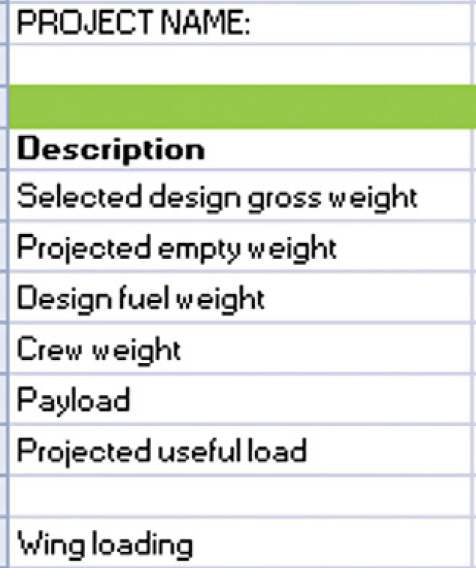
Das ist kein Truetype, OpenType oder Typ1-Font, sondern eine Pixelschrift.
Das bedeutet, das nicht die Außenkonturen der Buchstaben, sondern die einzelnen schwarzen Pixel als Bits in der Schrift gespeichert sind.
Vor Einführung der Truetype-Schriften waren diese auch auf dem PC die gängige Schrifart, und wurden auch von allen Anwendungen unterstützt. Heute noch ist mit dem Betriebssystem eine ganze Reihe dieser Pixelschriften installiert, um so auch alte Software zu unterstützen. Von Grafik, DTP  und Textverarbeitungprogrammen können diese jedoch heute nicht mehr genutzt werden. Bondrucker jedoch verwenden diese wegen der einfachen Umsetzung zum Druck noch immer.
Es gibt zwar einige Trutype-Schriften, die das Erscheinungsbild von Pixelschriften nachzuahmen versuchen, da dann aber die Konturen dieser Rechtecke fast nie mit dem Ausgabe-Raster übereinstimmz, ist deren Bild, gerade auf Bildschirmen zumeist recht unsauber.